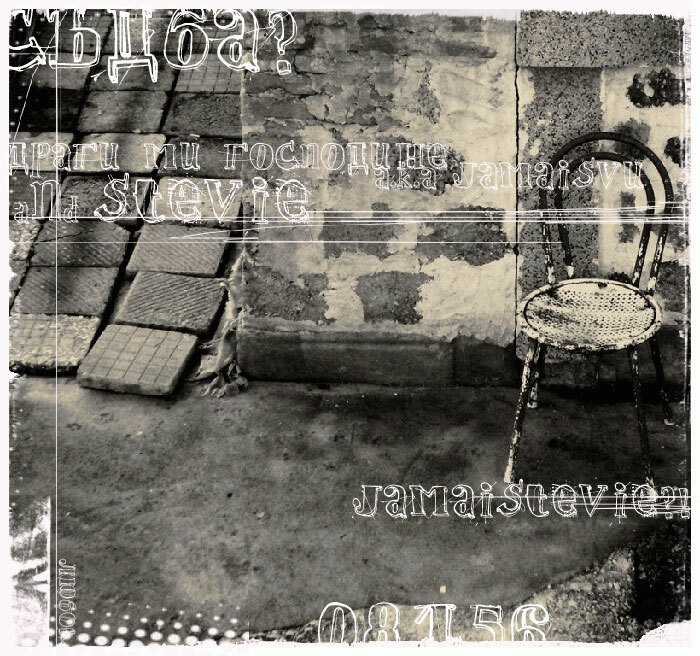
Jamaistevie to darmowy, konturowy font typu display, utrzymany w niespokojnym, ręcznie rysowanym stylu wiktoriańskim. Litery łączą w sobie miękkie zawijasy i ostre, szeryfowe kształty z luźnymi, przecinającymi się bazgrołami – dzięki temu font przypomina coś pomiędzy ozdobną kaligrafią a eksperymentem na marginesie notatnika.
To sprawia, że naturalnie pasuje do okładek zinów, plakatów zespołów, sesji modowych, tytułów i opakowań, które potrzebują odrobiny nerwowego, domowego dramatyzmu. Jako darmowy font, najlepiej sprawdza się w krótkich nagłówkach, monogramach czy inicjałach, gdzie te druciane sploty i nierówne kontury mogą dojść do głosu.